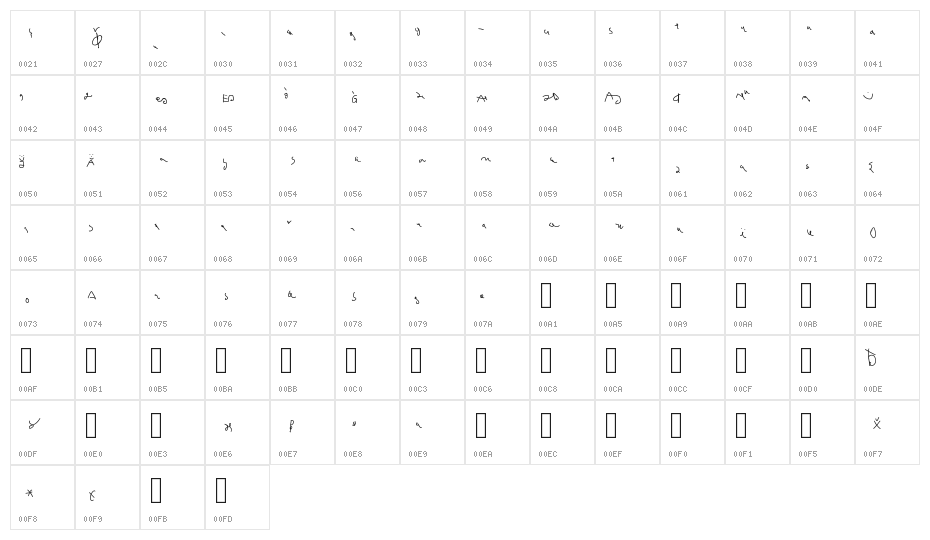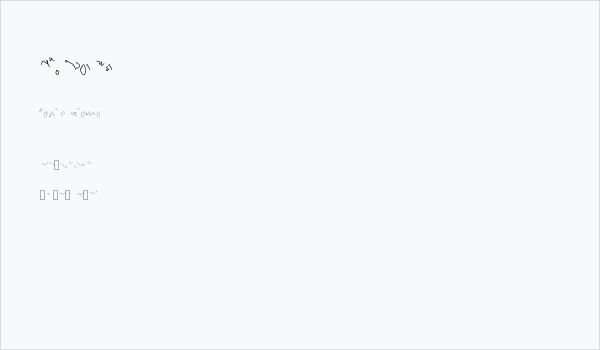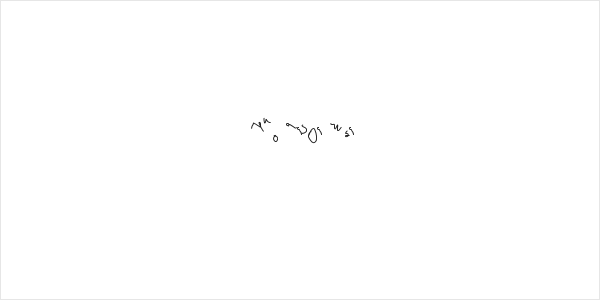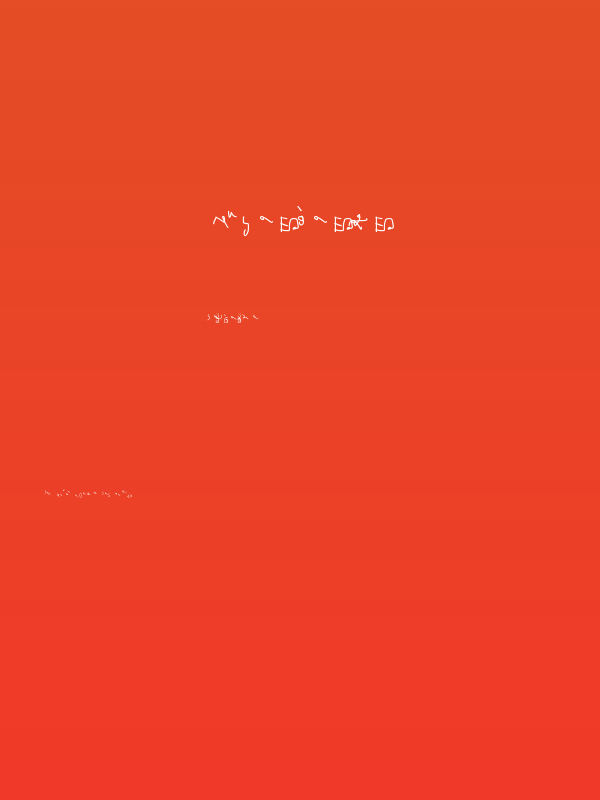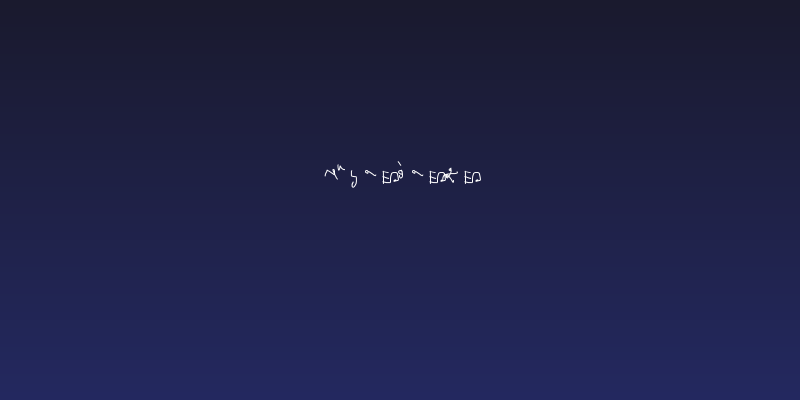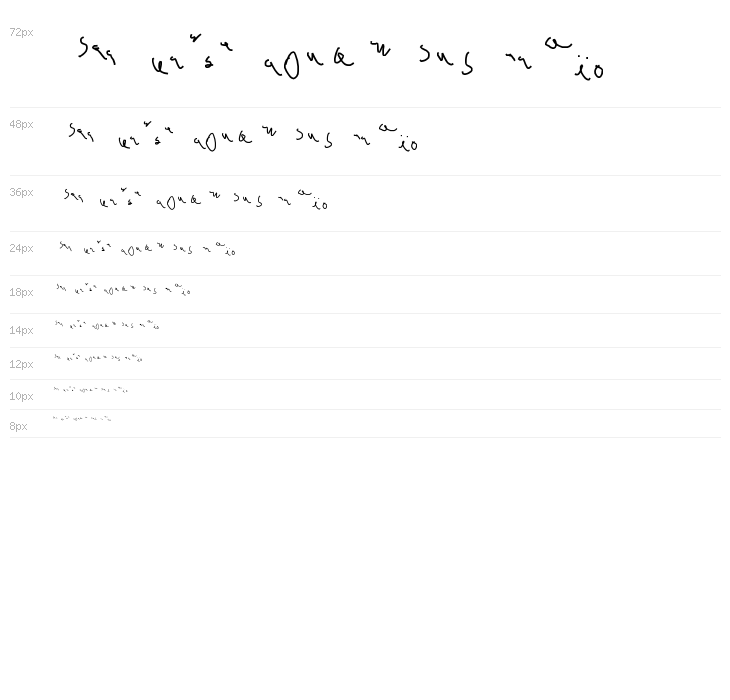
MsRefrence Font
| Stil general | Decorative, Abstract, Experimental |
| Caz de utilizare | Art projects, experimental design, not suitable for body text or standard communication. |
| Proiecte propuse | Experimental art, abstract posters, avant-garde zines, conceptual design projects. |